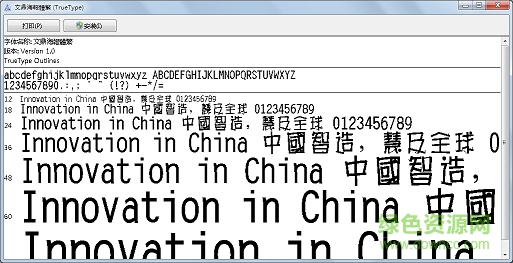
pop1eg bold t gb字體是一款風(fēng)格獨(dú)特的文鼎海報(bào)繁體,字形歪歪扭扭,筆畫較隨意,一般都是用在海報(bào)設(shè)計(jì)中,顯得非常特別,需要繁體字體的朋友快來(lái)下載吧!
海報(bào)體介紹
海報(bào)字體,是從用刷子隨意書寫的海報(bào)字形象演化而來(lái)。所以也叫隨意體。橫不平,豎不直,結(jié)構(gòu)也不規(guī)范(例十八)。
其藝術(shù)風(fēng)格:詼諧、隨意、俗野、怪異。